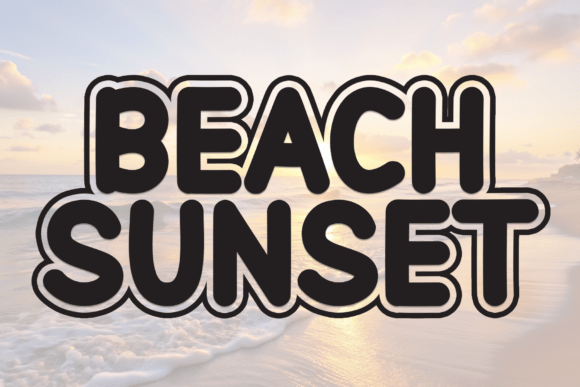
Beach Sunset
適切なデザイン要素を見つけるのは難しい場合がありますが、Beach Sunsetは作品を即座に引き立てる優れたコレクションを提供します。
POD(オンデマンド印刷)製品、結婚式の招待状、またはソーシャルメディアのグラフィックを作成している場合でも、Beach Sunsetは理想的です。